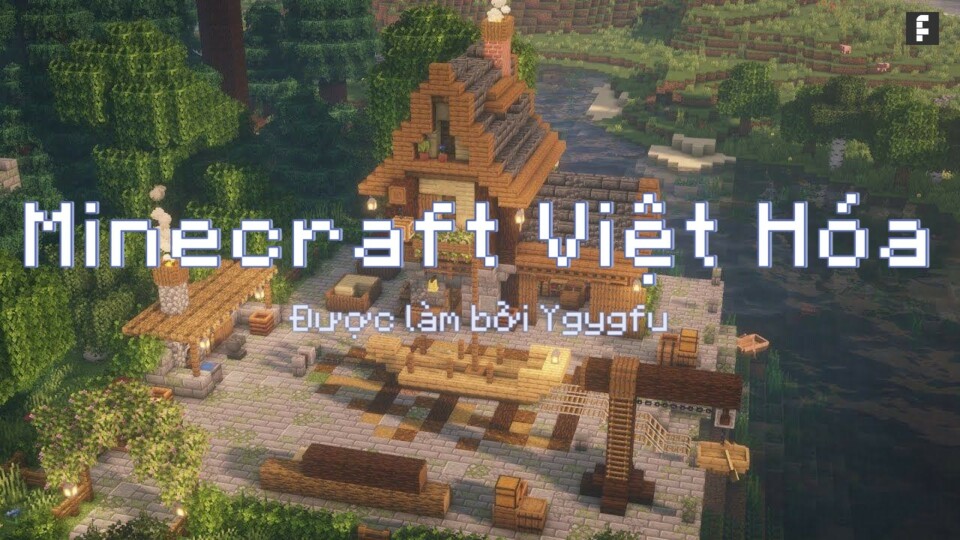
Font Việt Hóa Minecraft Seven
Dưới đây là một số đặc điểm nổi bật của font này:
1. Chữ viết rõ ràng: Font được tối ưu hóa để chữ viết có độ rõ nét cao, giúp người chơi dễ dàng đọc các thông tin trong game.
2. Tính thẩm mỹ: Với thiết kế gần giống như font gốc trong Minecraft, font Việt Hóa Seven giữ được phong cách pixel art đặc trưng của trò chơi, tạo cảm giác thân thuộc và phù hợp với bối cảnh.
3. Hỗ trợ tiếng Việt: Font này được bổ sung đầy đủ các ký tự tiếng Việt, bao gồm cả dấu câu và các ký tự đặc biệt, giúp người chơi dễ dàng giao tiếp và đọc hiểu trong game.
Font Việt Hóa Minecraft Seven là sự kết hợp hoàn hảo giữa tính năng và thẩm mỹ, mang đến cho người chơi một trải nghiệm thú vị hơn khi tham gia vào thế giới Minecraft.